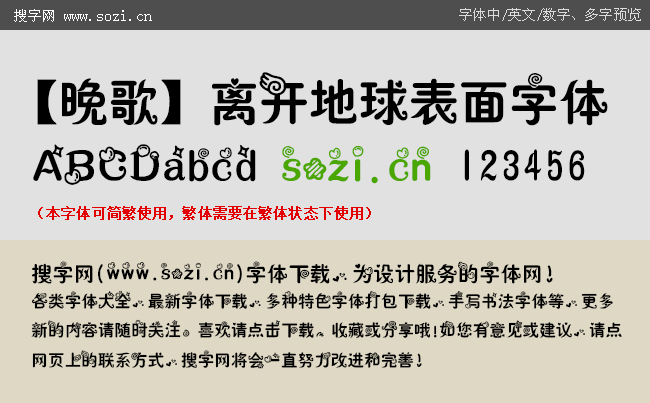
離開地球表面字體
搜字網(wǎng)給大家提供一款很卡通的手機(jī)中文字體下載。修改者給這款字體叫離開地球表面字體,這款字體以漢儀秀英體為原形,并配上多種可愛的卡通圖案,漢儀秀英體單字的點(diǎn)是心形桃點(diǎn),短撇為飄動(dòng)的柳葉形,非常可愛。該中文字體趣味性強(qiáng),非常適合喜歡卡通的朋友在手機(jī)上安裝使用。